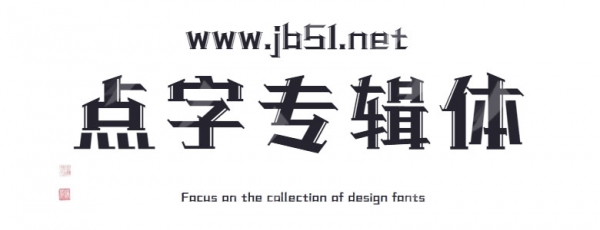
點(diǎn)字專輯體是由點(diǎn)字庫推出的藝術(shù)字體,字體融入了一些哥特體的設(shè)計裝飾,適合應(yīng)用于藝術(shù)設(shè)計、各類廣告和產(chǎn)品包裝設(shè)計等領(lǐng)域。
一款裝飾性的美術(shù)字體,設(shè)計靈感來自一些歌曲專輯的封面海報。在設(shè)計上,保證字體識別性前提下,融入了一些哥特體的設(shè)計裝飾,適用于廣告標(biāo)題、產(chǎn)品包裝、影視海報等應(yīng)用場合